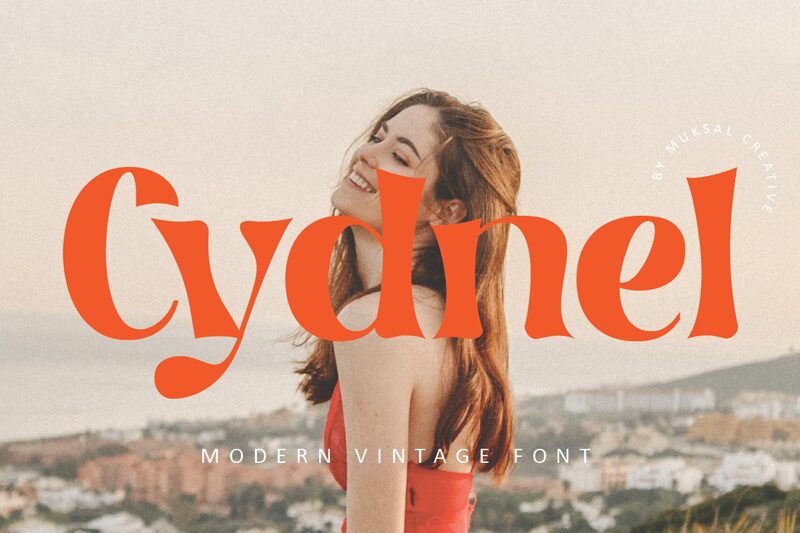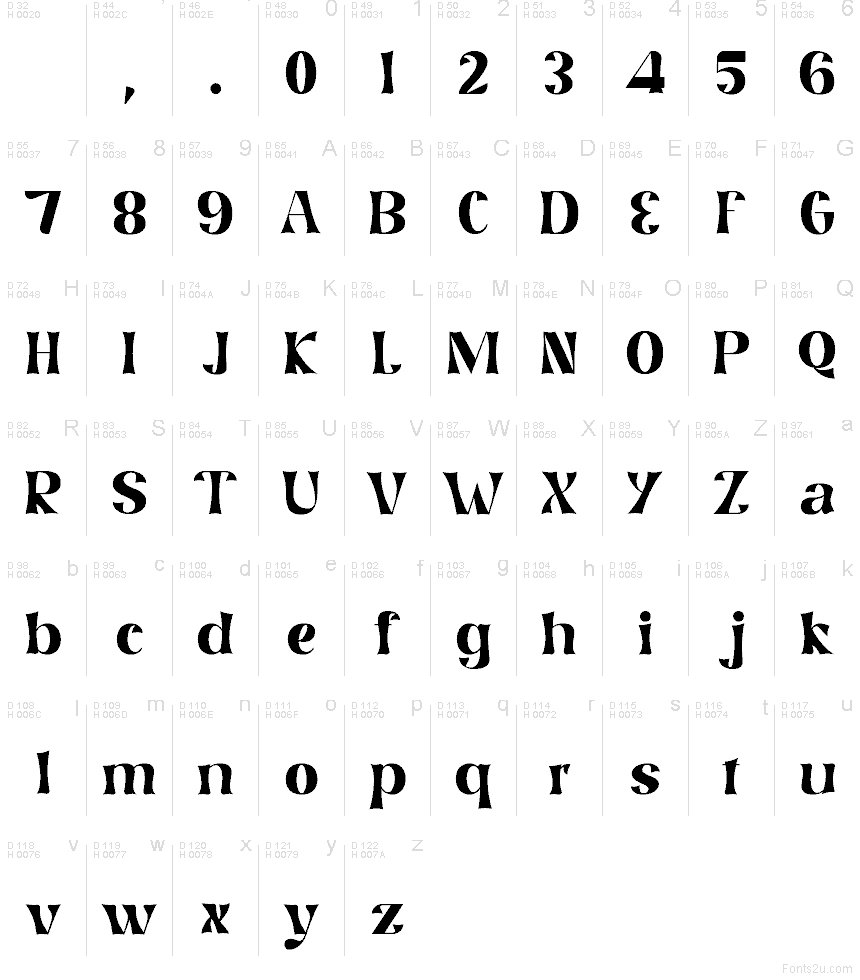
Cydnel Regular
Cydnel, bezplatné retro písmo od Benya Muksal Craeative, zaujme svojou vysokou, houpavou siluetou, ktorá akoby vypadla z knižných obálok a plagátov minulej éry. Písmená striedajú široké zaoblené tvary s úzkymi spojmi, zatiaľ čo klesajúce krivky a ostré výbežky dodávajú celému dizajnu teatrálny, až rozprávkový rytmus.
Tento tvar skvele funguje v brandingu kaviarní, butikovom balení, na plagátoch akcií, obaloch albumov alebo vo výrazných nadpisoch, kde písmo potrebuje rýchlo nastaviť osobitý tón. Krátke titulky ťažia najmä z jeho rozmáchlých spodných ťahov a jasného kontrastu, ktoré vytvárajú dekoratívnu linku bez nutnosti ďalších ozdôb.